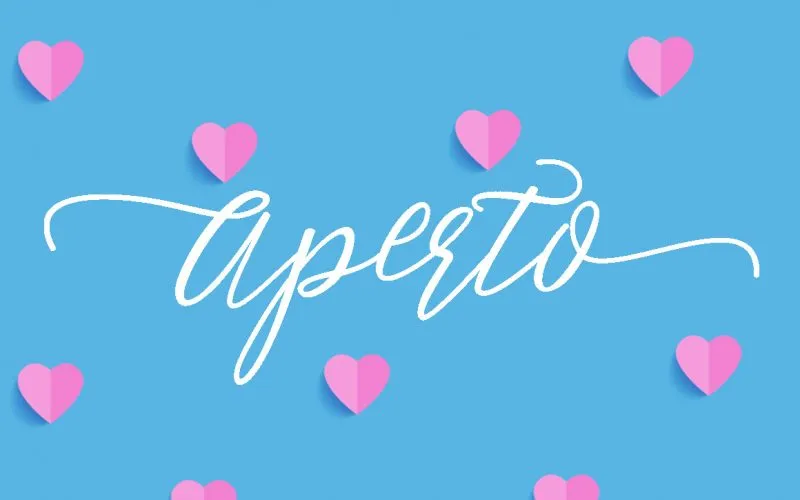
Aperto Script Font é uma elegante fonte escrita à mão criada pelo designer Hamilton para quem busca adicionar um toque único aos projetos de letras e a suas marcas. Suave como o trigo, esta fonte foi cuidadosamente desenvolvida com curvas suaves, garantindo um resultado que seja inteiramente original e distintivo. Ideal tanto para criar logomarcas e identidades de marca quanto para aplicar em fotografias, marcas de água, postagens nas redes sociais, anúncios, convites, designs de produtos, etiquetas, estilismo de festa ou embalagens de produto — qualquer trabalho que exija uma paixão pela escrita à mão. Seja você um designer criativo ou um amante da arte gráfica, Aperto Script Font certamente encaixa perfeitamente na sua necessidade de expressar a personalidade única dos seus projetos.